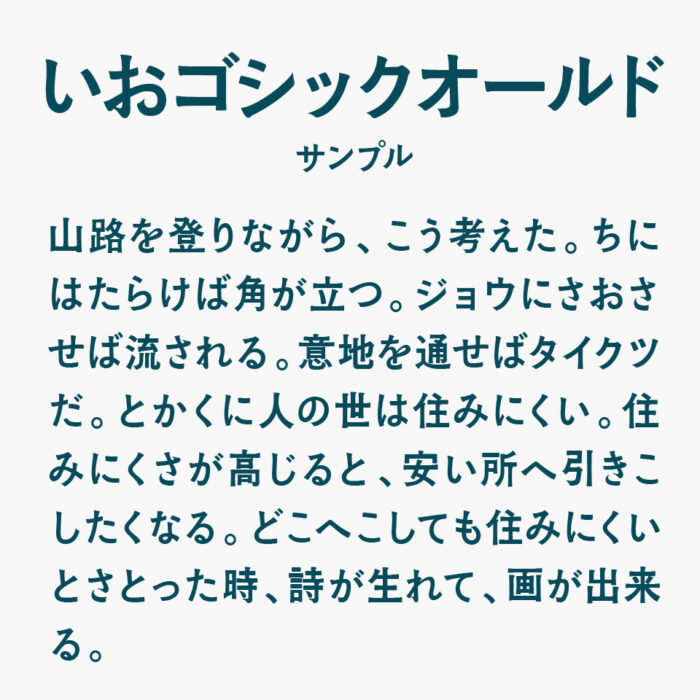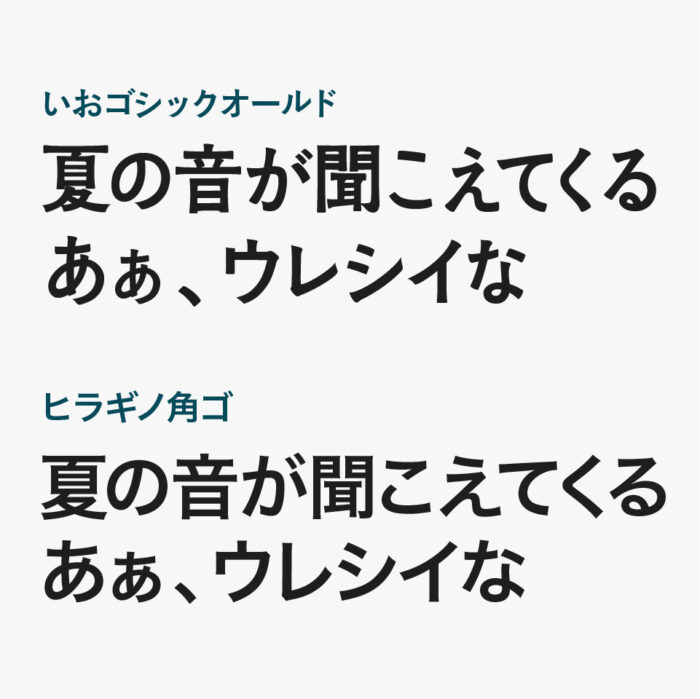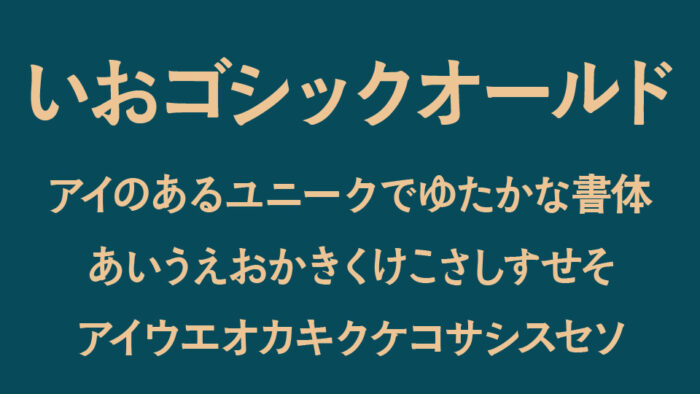
いおゴシックオールドフォントは、現代的なゴシック体にわずかなクラシカルなエレメントを残した、落ち着きと安定感の佇まいのあるゴシック体フォントです。
横線と縦線のバランスが絶妙で、読みやすさに優れながらも堅苦しくなりすぎない雰囲気を保っています。
一般的なゴシック体フォントに比べると、落ち着きのあるクラシカルなスタイルがとても素敵です。見出しやタイトルなどにもぴったりです。